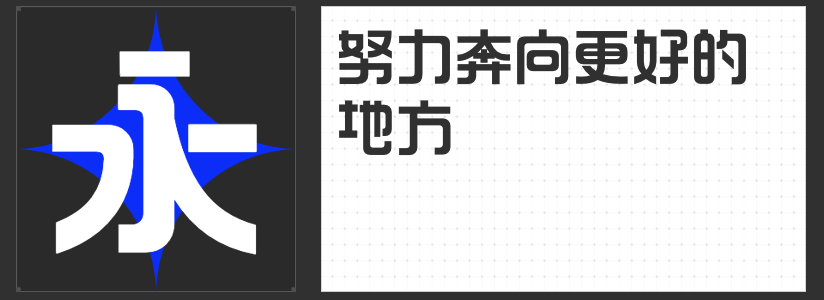
四款创意黑体推荐:让海报设计瞬间破圈的视觉利器
在信息爆炸的视觉时代,海报设计的核心在于用独特字体抓住受众的第一眼注意力。以下四款非免费创意黑体,以极具辨识度的造型语言与结构巧思,为品牌传播注入强烈的视觉张力。
灵感源自日本地铁工作者佐藤修悦的胶带指路艺术,这款字体将人工拼贴的几何美学发挥到极致。方正字框内,平直切口与不规则留白形成动态平衡,笔画边缘的胶带质感带来手工温度。其重心多变的排版特性,既可营造工业风的冷峻秩序,又能通过错位排列制造戏剧性冲突,尤其适合需要制造视觉记忆点的活动海报与文创包装。
以极简主义重构汉字结构,棱角分明的直线笔画构建出未来感十足的几何矩阵。去钩设计与竖直撇捺处理打破传统黑体框架,镜像对称的视觉语言自带科技感。特别收录的叠字与自然元素符号,既满足社交媒体传播的网感需求,又为环保、科技类主题海报提供丰富的创意延展空间。
三、高手兵克侠客体
在横笔画两端融入古建筑飞檐的曲线美学,将国潮基因注入现代字体设计。上扬的起收笔处理既保留了书法的韵律感,又通过标准化设计确保远距离识别度。这款字体在复古餐饮、文化展览等场景中,能瞬间唤起受众对传统文化的情感共鸣。
6度倾斜设计赋予静态文字动态势能,硬朗的直线笔画与均匀布白构建出强烈的视觉推进感。中英文符号的同步倾斜处理,确保多语言排版时的整体性。这款字体在运动品牌、音乐节等需要传递速度感与力量的场景中,能形成极具冲击力的视觉风暴。
这四款字体通过解构与重构汉字形态,在保证可读性的基础上,为设计师提供了突破常规的创意工具。它们不仅是信息载体,更是能独立表达品牌态度的视觉符号,让每一张海报都成为穿透信息噪声的视觉宣言。